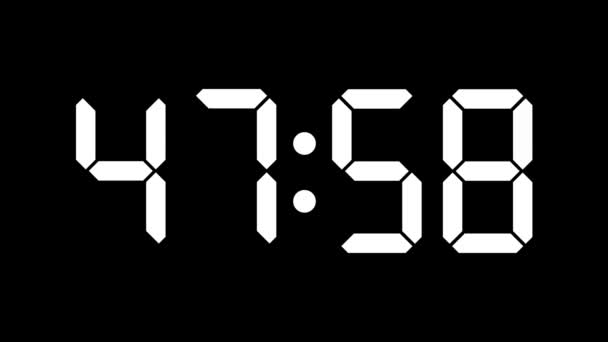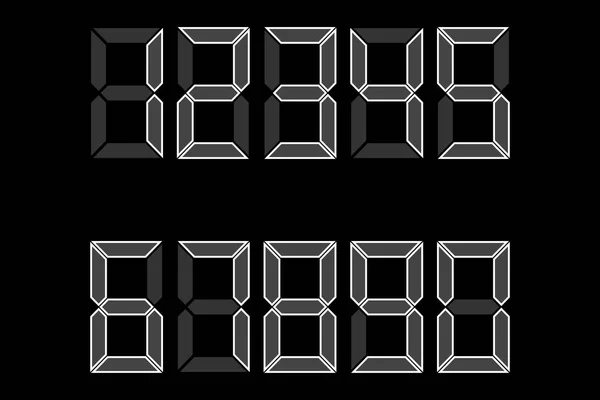
Шрифт цифр как на электронных часах
В этой статье мы попросили мастера ответить на вопрос: «Шрифт цифр как на электронных часах?», а также дать полезные рекомендации для наших читателей. Что из этого получилось, читайте далее.
У когонибудь есть или подскажите как называется ttf-шрифт как в электронных часах цыфры? Я нашел 2 шрифта: DS Crystal и a_LCDNova, но мне они не понравились. в первом единица как семерка такое ощущение, а во втором много «палочек». вот есть попроще у когонибудь шрифт электронных часов? чтобы например таже единица была просто прямой. ну как обычно в часах )))
Но если размер шрифта сделать меньше, чем у основного текста, то даже самый разборчивый шрифт будет сложно читать, расстояние между буквами будет слишком маленьким, внутрибуквенный просвет — слишком узким, а высота строчных литер — ничтожной. Сравните маленькие шрифты в этих двух примерах.
К счастью, шрифты были специально адаптированны под веб-страницы и хорошо показывают себя на любом устройстве.
Семейство шрифтов ScreenSmart создано для того, чтобы восполнить недостатки небольшого размера.
Выше представлены два типа верстки, где используется семейство шрифтов Whitney, и справа для примечания мелким шрифтом под графиком использован Whitney ScreenSmart. Шрифты ScreenSmart всегда дают большую чёткость, их комфортнее читать, а значит, они отлично подойдут для мелкого написания.
Мелкий шрифт — проклятие типографики, и дело не только в его размере, но и в большом объёме информации. Пояснения, заявления об ограничении ответственности и списки ингредиентов чаще всего игнорируются читателями, однако их можно отнести к наиболее строго регламентируемым частям любого типографического объекта, а следовательно, это контент, который тщательно просматривается.